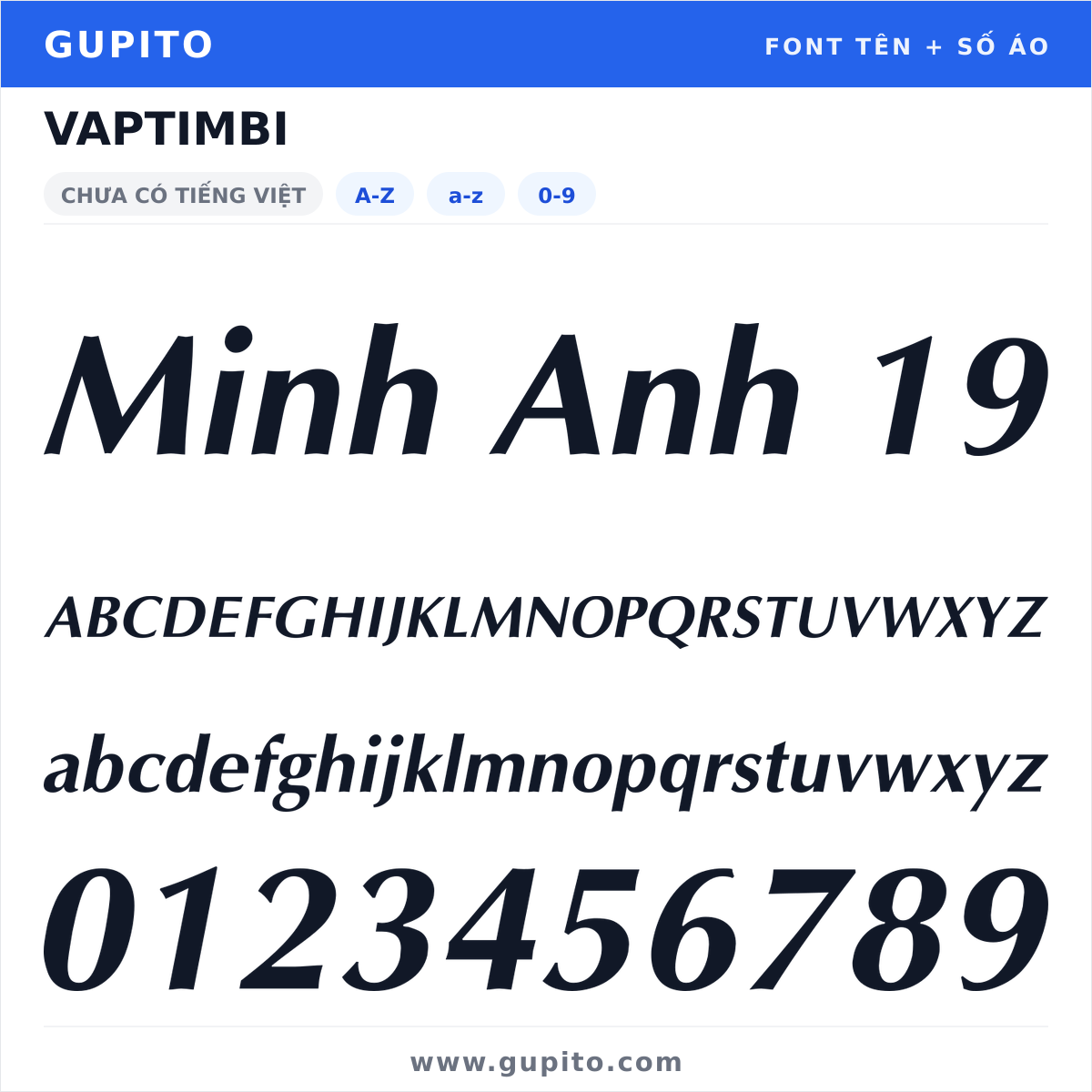
VNI-Aptima-Bold-Italic
VNI-Aptima-Bold-Italic · Font VAPTIMBI in tên áo bóng đá, số áo thể thao · chữ nghiêng đậm
Font VAPTIMBI với nét chữ đậm, nghiêng, có bảng số 0-9, phù hợp in tên và số áo bóng đá, áo lớp, quà tặng. Bộ chữ VNI-Aptima-Bold-Italic dùng để in chuyển nhiệt lên áo đấu, áo lớp, áo nhóm và đồ thể thao theo yêu cầu. Kiểu dáng: chữ nghiêng đậm. Font dùng cho chữ không dấu và số áo. Có đủ bộ chữ số để in số áo. Từ khoá liên quan: font vap-tim-bi, font in tên áo, font in số áo, font áo bóng đá, font áo thể thao, font chữ nghiêng, font chữ đậm, font có bảng số.